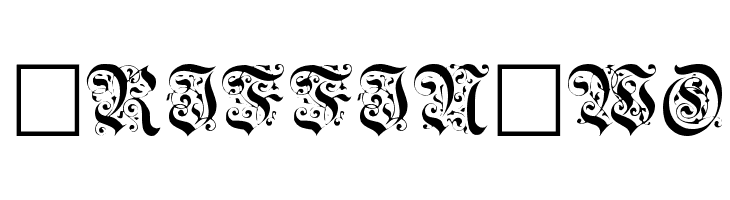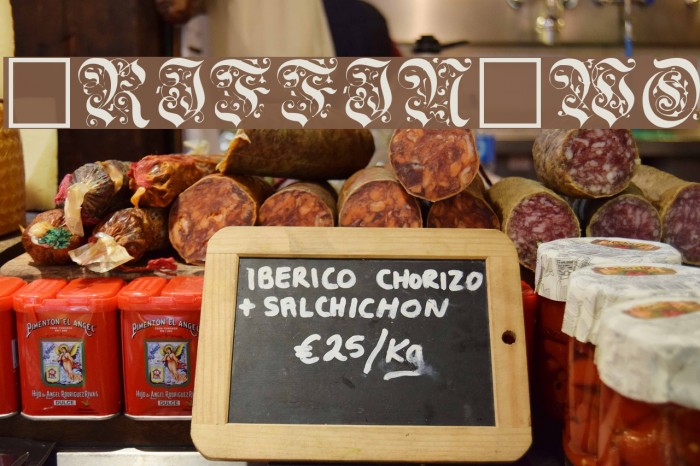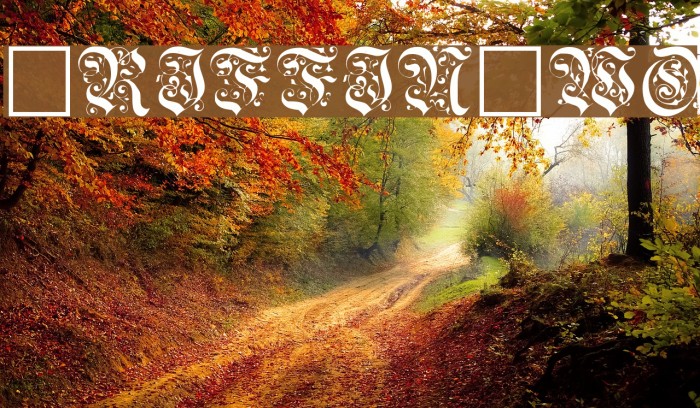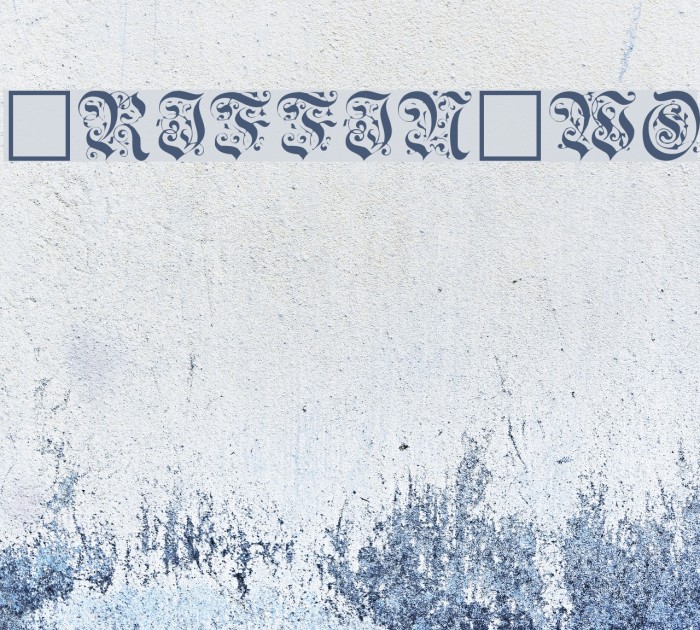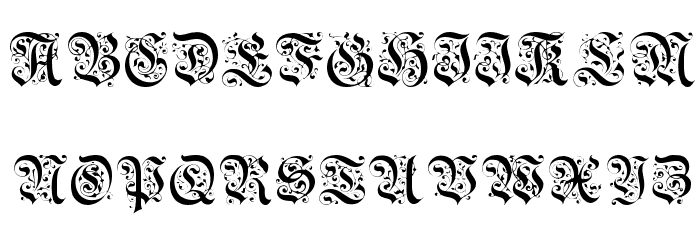
GriffinTwo Font
✎ Gothic
| الفئات | Gothic |
| النمط العام | Vintage |
| مشاريع مقترحة | Ideal for vintage-themed designs, wedding invitations, posters, and branding that requires a touch of elegance and sophistication. |